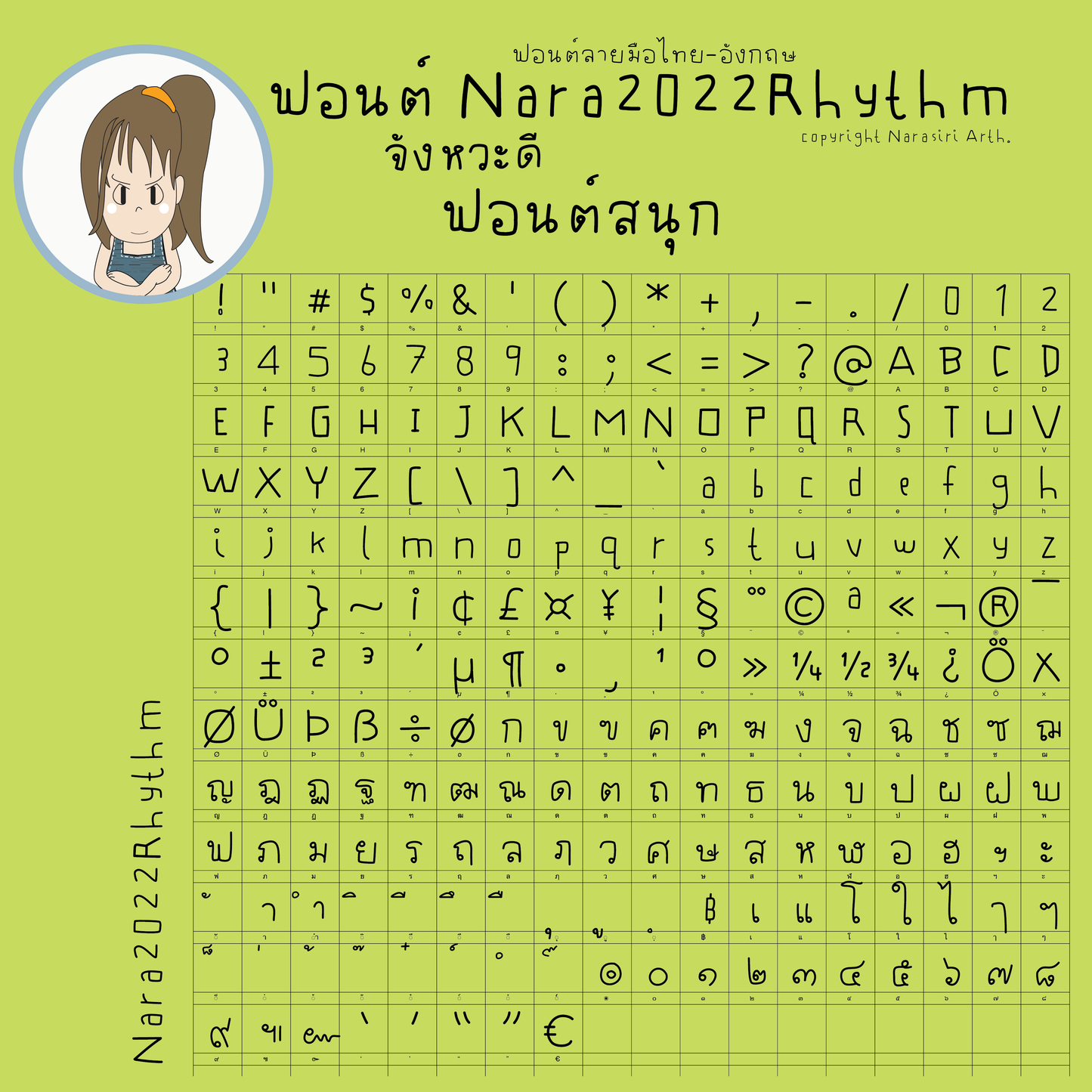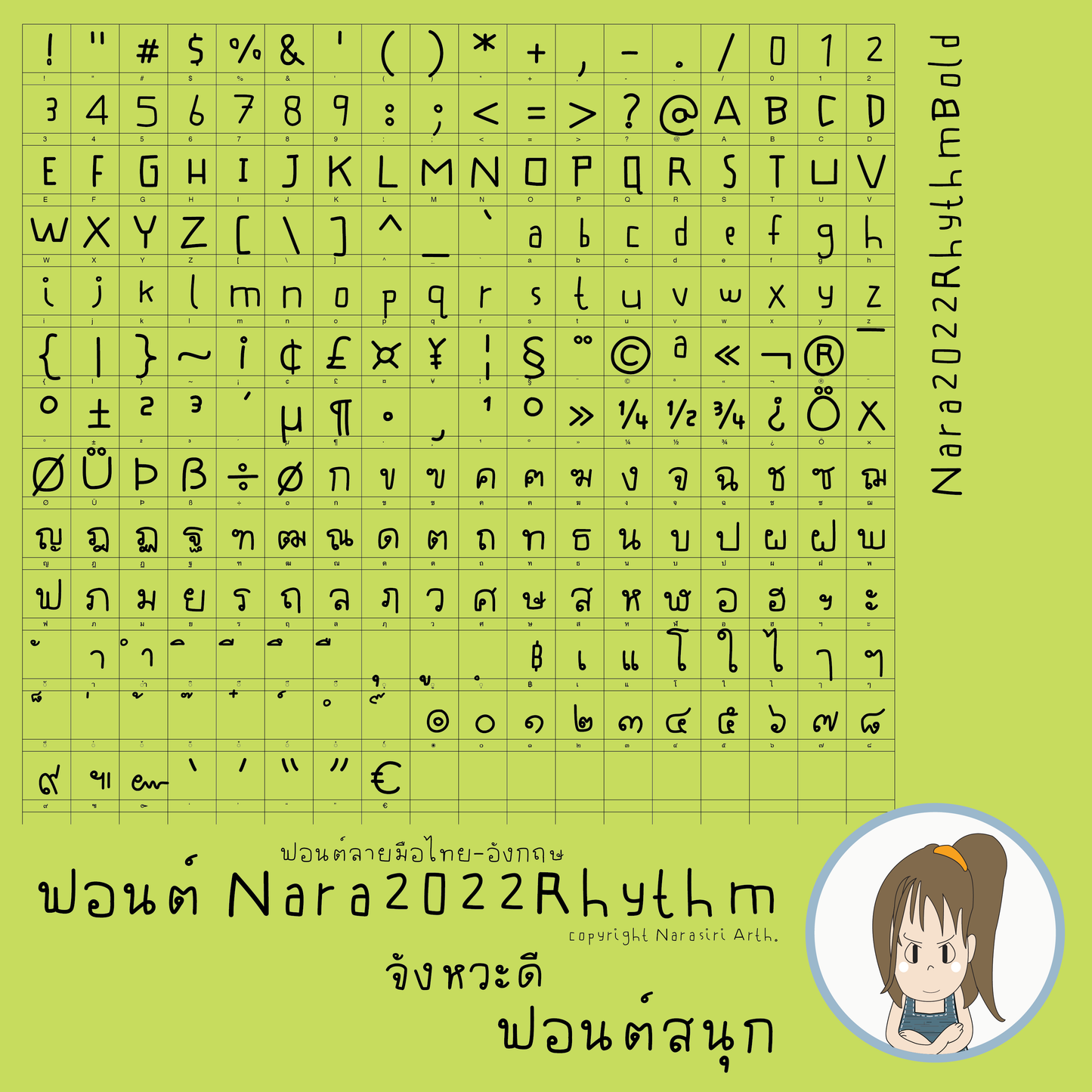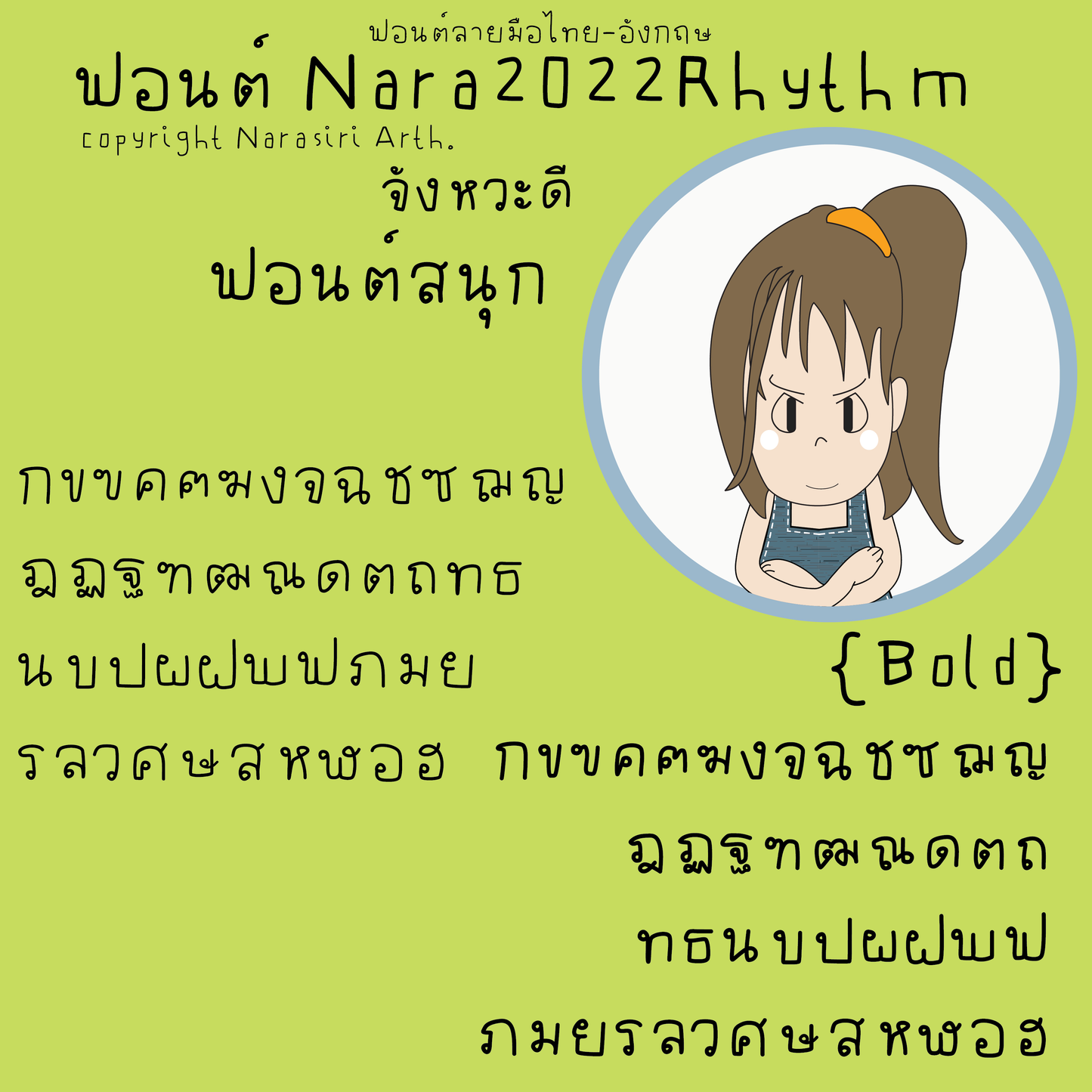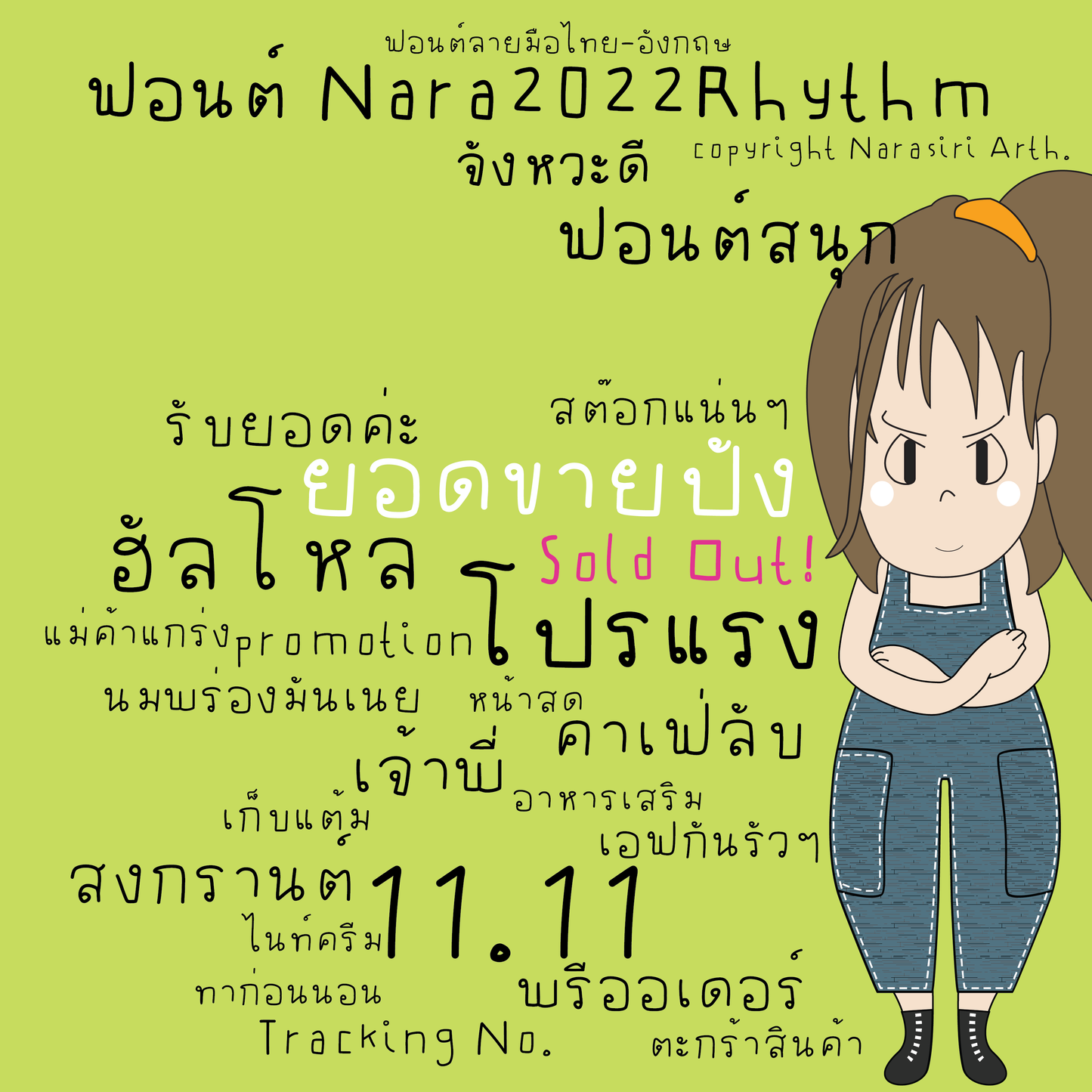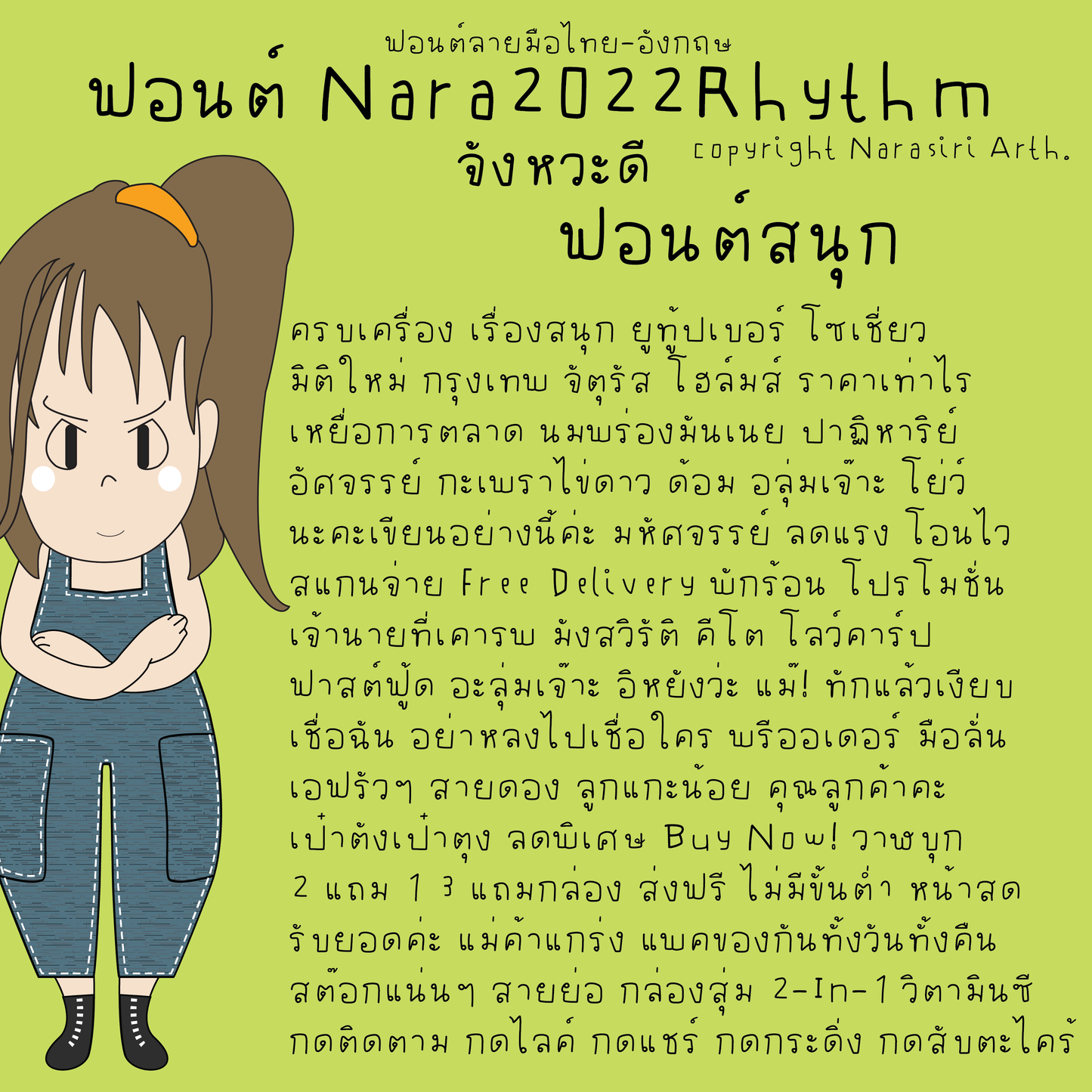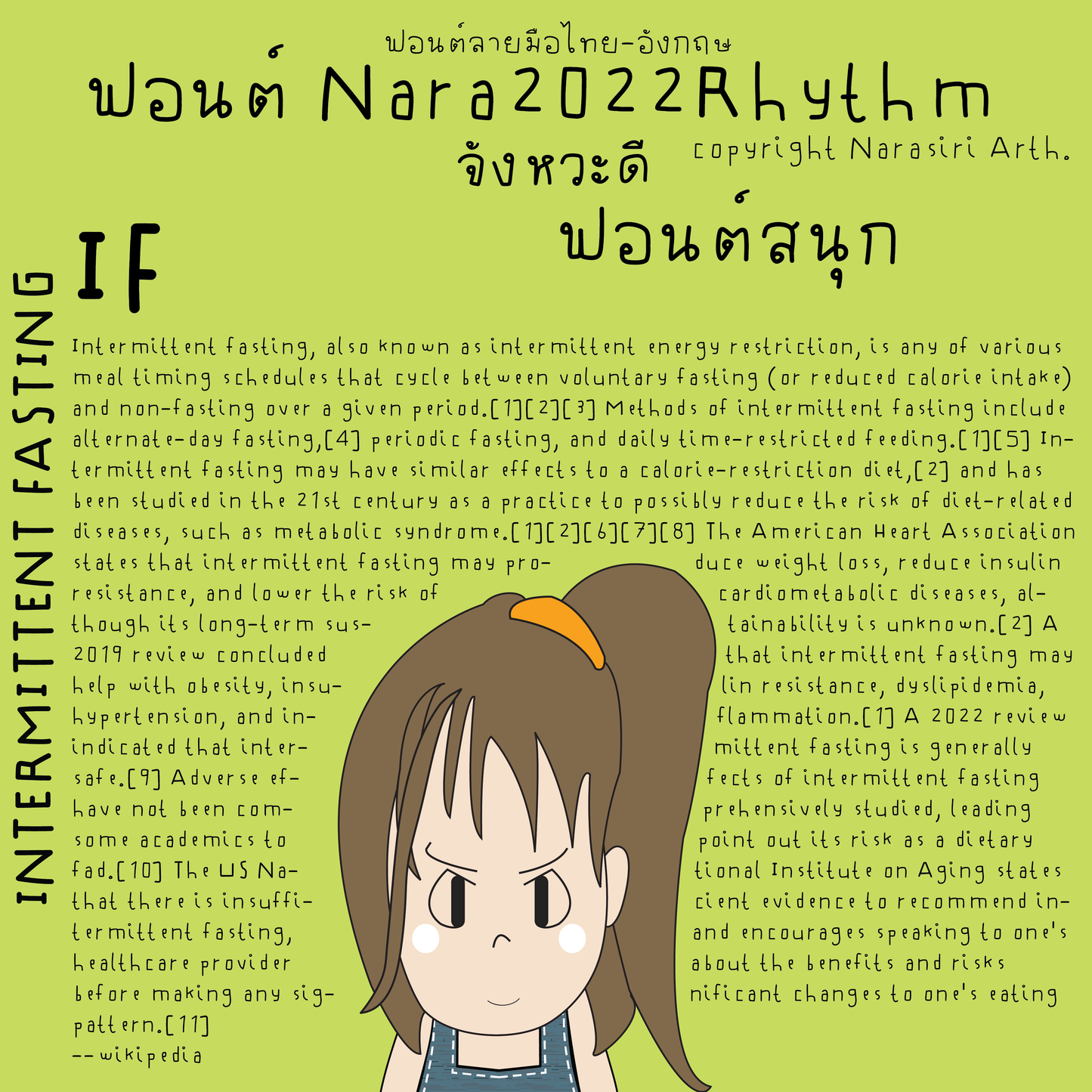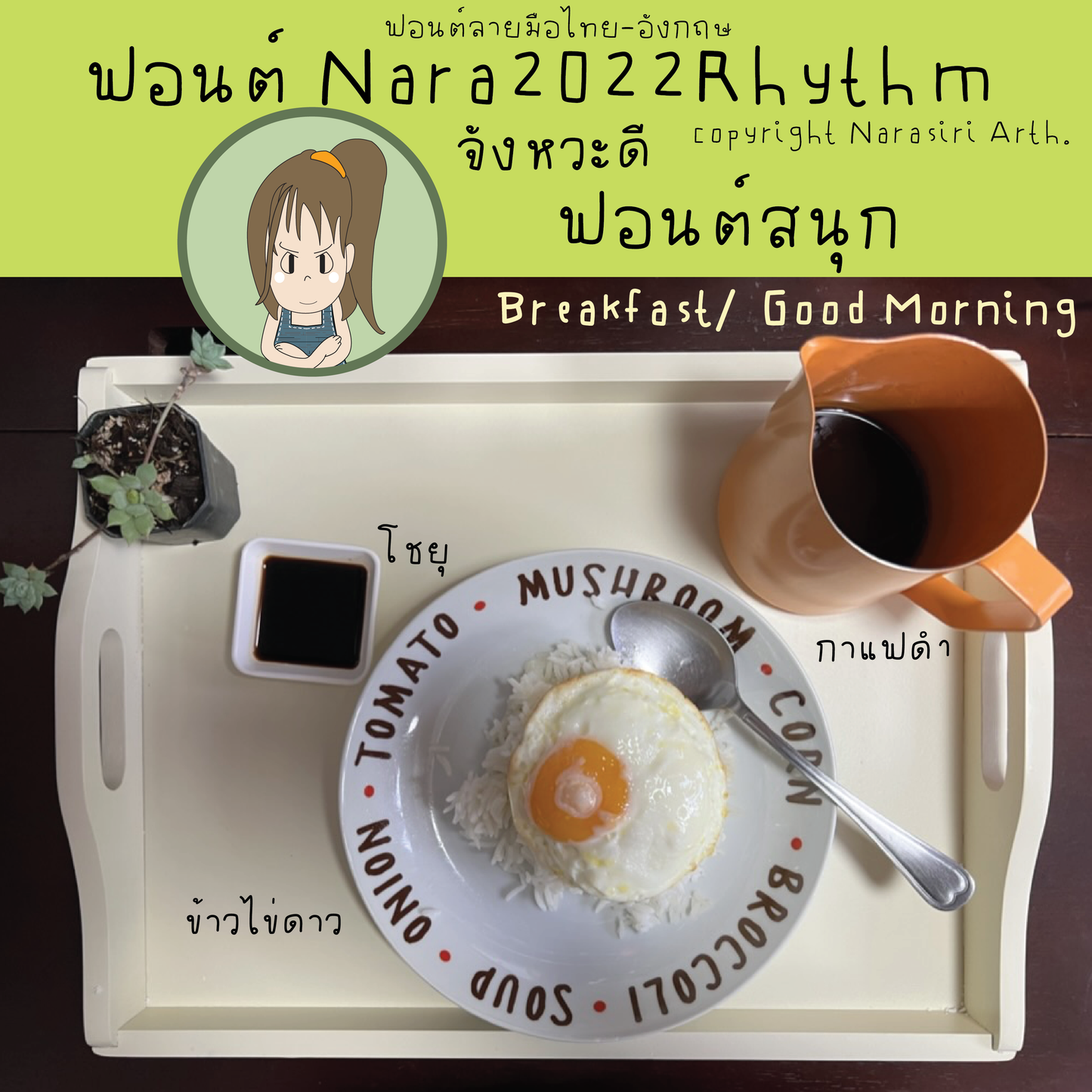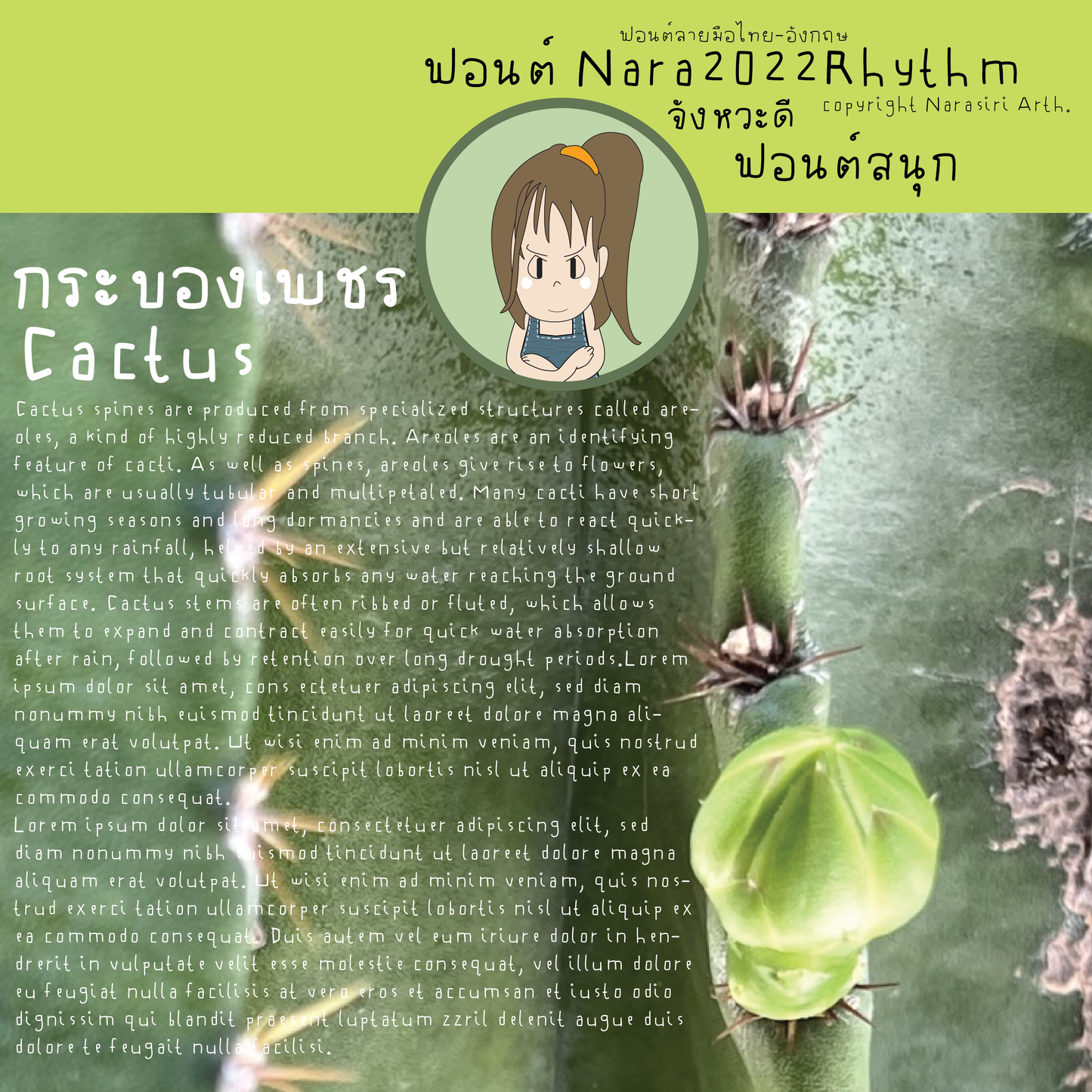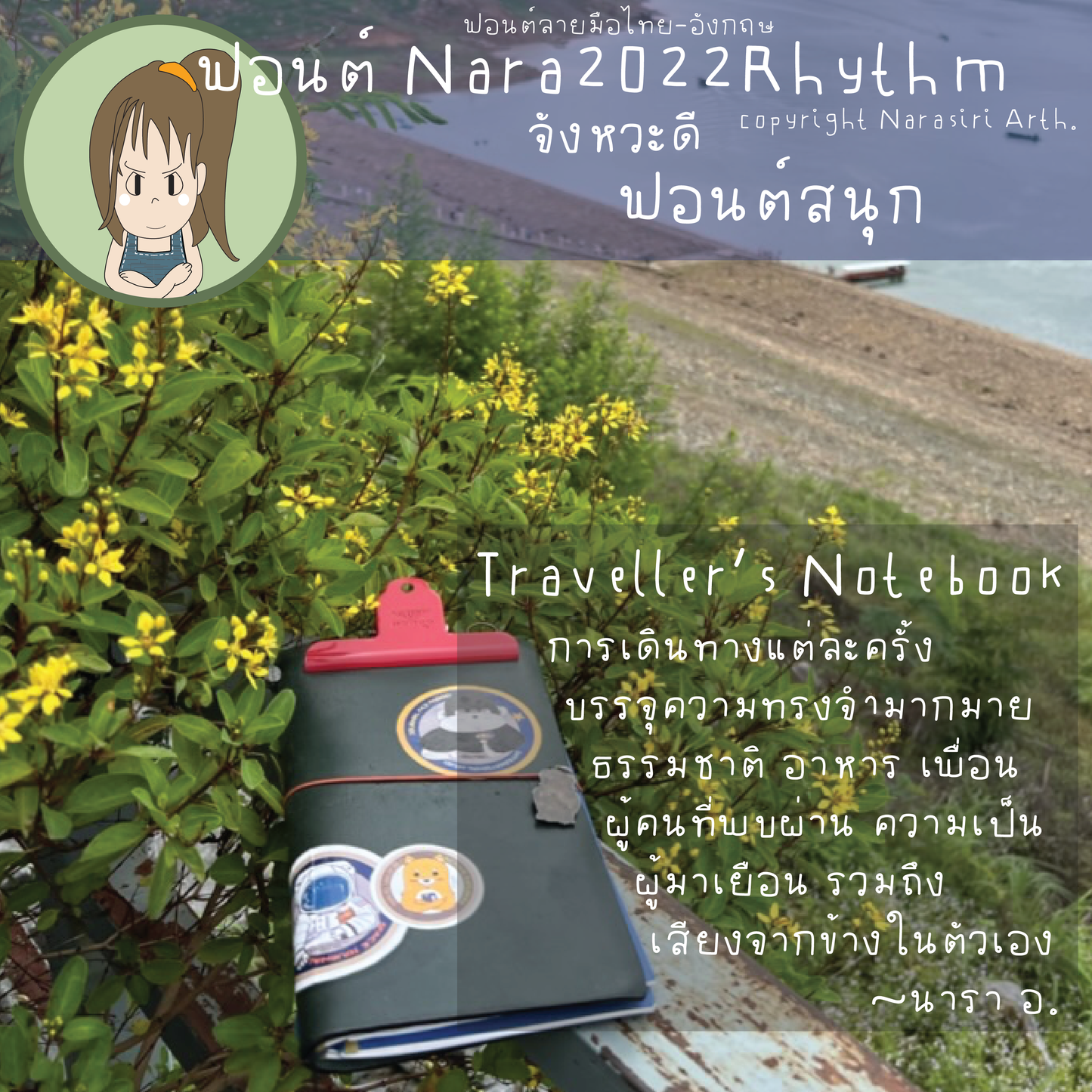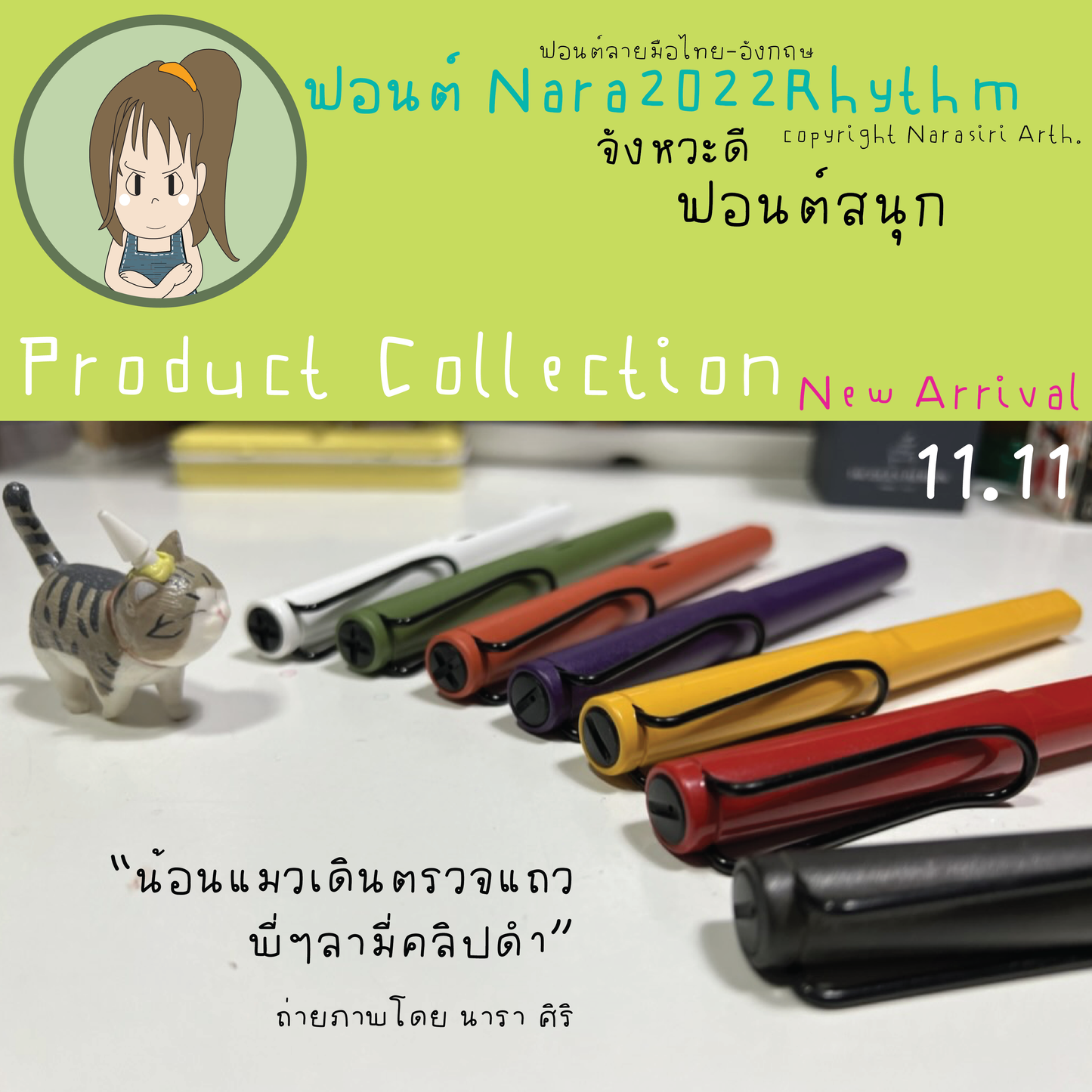
Nara2022Rhythm Font, Informal Handwriting Thai & English Font
NaraRhythm ฟอนต์ลายมือ ภาษาไทย-อังกฤษ ลายมือเขียนแบบไม่เป็นทางการ จังหวะดี ฟอนต์สนุก
แรงบันดาลใจในการออกแบบ
อยากได้ฟอนต์ที่ดูสนุก มีจังหวะ กระโดดโลดเต้น น่าอ่าน ดูมีเอนเนอร์จี้ ถ้าได้เอาไปใช้ทำ artwork คงสนุกน่าดู : )
Creator's Inspiration
Thinking about cute fonts jumping by their rhythm ... it might be fun reading these fonts : )